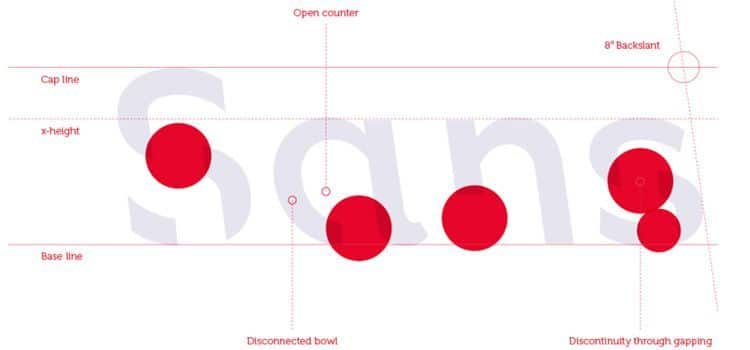
«Sans Forgetica», la tipografía que te ayuda mejorar la memoria
«Sans Forgetica» es una tipografía ideada por la universidad de Melbourne para mejorar la memoria.
Seguramente nos habrá pasado a todos mientras estudiábamos. La falta de interés y el cansancio nos pasaba factura y hacía que no retenieramos los textos que leíamos. En consecuencia no nos recordábamos de ellos y teníamos problemas a la hora de realizar los exámenes.
Un problema al que han querido poner solución en la universidad de Melbourne. Un equipo de investigadores de la RMIT de Melbourne han creado una tipografía que aseguran podría acabar con el fracaso escolar y la falta de memoria. La tipografía se llama «Sans Forgetica».
Esta tipografía tiene la peculiaridad que tiene una inclinación de siete grados hacia la izquierda y huecos en cada letra. Según el profesor de tipografía Stephen Banham: «La mente buscará completar esas formas y, al hacerlo, retrasará la lectura y activará la memoria».
«Cuando queremos aprender algo y recordarlo, es bueno que se agregue un poco de obstrucción a ese proceso, sino es demasiado fácil y no crea un rastro de memoria» explicó Janneke Blijlevens, otro de los responsables del proyecto.
En un estudio realizado a 400 estudiantes se concluyó que gracias a la «Sans Forgetica» se retenía un 57% de información que con la Arial, que era de un 50%. Esta tipografía se diseñó para que los estudiantes pudieran preparar mejor sus exámenes, pero se está considerando ampliar su uso a otros ámbitos, como ayudar a las personas mayores con los problemas de memoria.